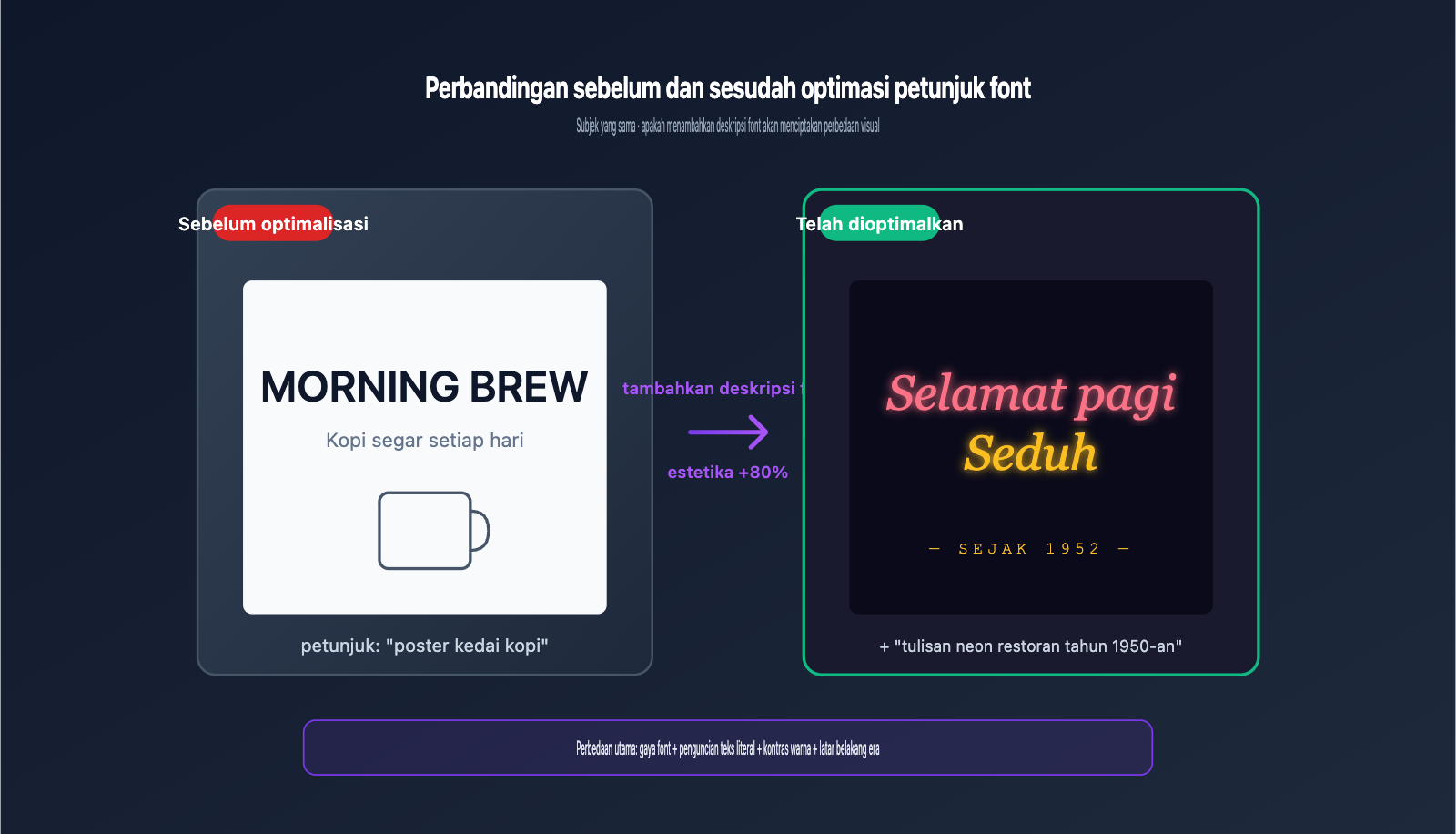
Banyak pengguna yang menggunakan API gpt-image-2 atau membuat gambar melalui situs resmi ChatGPT sering menghadapi masalah yang sama: meskipun teks yang dihasilkan model sangat mudah dibaca, jenis hurufnya selalu berupa font sans-serif sederhana bergaya "estetika insinyur" yang terasa kurang memiliki nilai desain atau identitas merek. "Estetika sederhana" ini sangat terasa saat membuat poster, sampul media sosial, atau gambar promosi produk, sehingga membuat komposisi yang sebenarnya bagus jadi terlihat murahan.
Akar masalahnya bukan pada kemampuan model, melainkan karena sebagian besar pengguna hanya mendeskripsikan "apa yang digambar" dalam petunjuk mereka, tanpa memberi tahu model "seperti apa seharusnya tampilan font tersebut". Artikel ini disusun berdasarkan Cookbook resmi OpenAI dan pengalaman pengujian nyata dari berbagai penyedia layanan API. Kami akan membedah mekanisme kerja petunjuk font gpt-image-2, memberikan 6 templat deskripsi font yang siap pakai, serta menggabungkannya dengan contoh pemanggilan di platform APIYI (apiyi.com) untuk membantu Anda mempelajari cara menulis petunjuk agar font hasil gambar benar-benar "estetik" dalam 5 menit.
Satu: Mekanisme Inti Petunjuk Font gpt-image-2
1.1 Mengapa font default selalu sans-serif yang sederhana?
Tanpa deskripsi font yang jelas, gpt-image-2 akan menghasilkan font berdasarkan prioritas visual "paling aman" dalam data pelatihannya. Hasilnya sering kali berupa font sans-serif geometris netral (mirip gaya Inter atau Helvetica), yang menjamin keterbacaan namun mengorbankan ekspresi gaya.
Panduan petunjuk resmi OpenAI menyatakan dengan jelas: model hanya akan merender atribut visual yang Anda batasi secara aktif, sementara bagian yang tidak dibatasi akan menggunakan nilai default. Artinya, jika Anda hanya menulis "poster tentang kopi", model akan otomatis memilih font yang paling umum. Hanya ketika Anda menulis detail seperti "hand-lettered display serif with thick brushstrokes", model akan memicu prioritas font yang sesuai.
Itulah mengapa untuk tema dan panjang petunjuk yang sama, kualitas gambar dengan deskripsi font dan tanpa deskripsi font bisa berbeda jauh. Setelah memahami hal ini, "font yang terlihat sederhana" bukan lagi cacat model, melainkan karena pengguna belum mendeskripsikan font sebagai informasi inti dari gambar.
Faktor lain yang sering diabaikan adalah versi model. Peningkatan terbesar gpt-image-2 dibandingkan generasi 1.5 terletak pada lapisan rendering teks, yang mendukung output hingga 4K secara native, dengan kemampuan pemrosesan yang jauh lebih baik untuk teks kecil, tata letak padat, dan campuran berbagai font. Ini berarti upaya yang Anda habiskan untuk petunjuk font di gpt-image-2 akan memberikan hasil yang jauh lebih sepadan.
1.2 Empat Elemen Inti Petunjuk Font gpt-image-2
Jika kita membedah "deskripsi font", gpt-image-2 sebenarnya merespons instruksi dalam empat dimensi independen yang tidak boleh terlewatkan:
| Elemen | Peran | Contoh Deskripsi |
|---|---|---|
| Gaya Font (Style) | Menentukan struktur bentuk huruf & karakter visual | bold sans-serif, condensed serif, hand-lettered display |
| Hierarki Ukuran (Hierarchy) | Mengontrol kontras judul/subjudul/teks isi | large headline, small body copy |
| Kontras Warna (Contrast) | Menentukan keterbacaan antara font & latar belakang | high contrast white on navy |
| Tata Letak (Placement) | Mengunci posisi teks & perataan | centered at top, clean kerning |
1.3 Cara Penulisan dengan Batasan Teks yang Kuat
Image-gen-models-prompting-guide dari OpenAI Cookbook memberikan tips kunci: bungkus string teks yang akan muncul di gambar dengan tanda kutip atau huruf kapital semua. Model akan memahami bagian ini sebagai batasan keras yang "harus dirender secara literal, tidak boleh salah atau kurang huruf".
Berdasarkan pengujian, menulis the word coffee on a sign dibandingkan dengan a sign with the EXACT text "COFFEE" menunjukkan perbedaan probabilitas kesalahan ejaan yang signifikan; yang terakhir hampir menjamin konsistensi tingkat karakter. Untuk nama merek yang sulit dieja (seperti Schønne atau APIYI), disarankan untuk memisahkan setiap karakter dengan spasi, misalnya "A P I Y I", untuk lebih mengurangi risiko kesalahan posisi karakter.
2. 6 Metode Praktis Menulis Petunjuk Font untuk gpt-image-2
Setiap skenario membutuhkan strategi deskripsi font yang berbeda. Berikut adalah 6 metode yang dirangkum dari contoh resmi OpenAI, pengujian praktis di fal.ai, dan pustaka prompt sumber terbuka yang sering digunakan dan dapat digunakan kembali.
2.1 Metode Deskripsi Fungsi: Cara Paling Stabil
Gunakan istilah tipografi untuk mendeskripsikan karakteristik bentuk huruf. Ini adalah metode yang paling direkomendasikan oleh OpenAI dengan tingkat keberhasilan tertinggi:
Font bukanlah dekorasi gambar, melainkan jiwa dari gambar tersebut. Menguasai penulisan petunjuk font gpt-image-2 pada dasarnya adalah memperluas "rekayasa petunjuk" dari tingkat komposisi gambar ke tingkat desain tipografi. Ini adalah lompatan kunci bagi pembuatan gambar AI dari sekadar "bisa dilihat" menjadi "tingkat profesional".